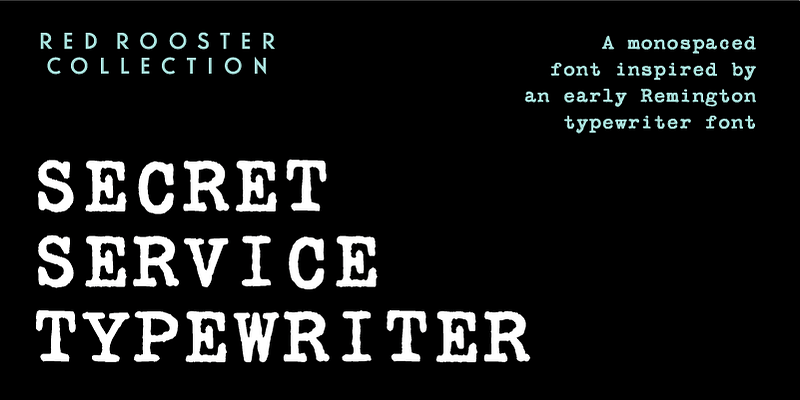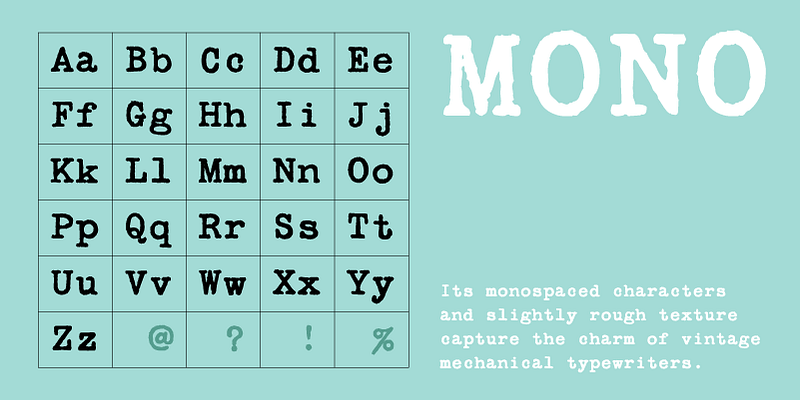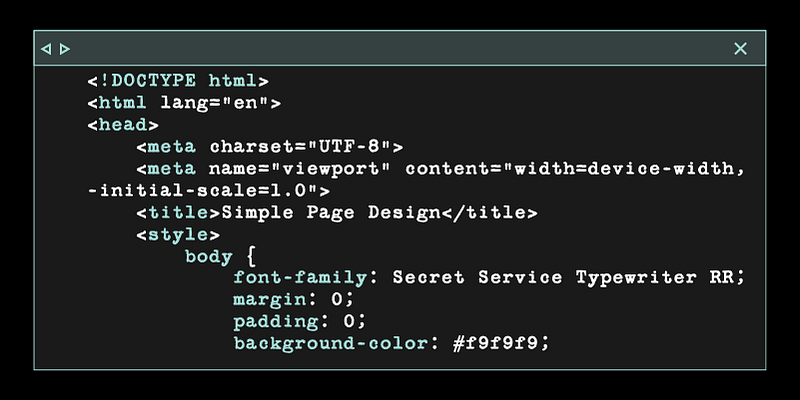
Die Secret Service Typewriter ist inspiriert von der Schreibmaschinenschrift Remington der Keystone Type Foundry aus dem Jahr 1905. Die nichtproportionalen Zeichen (Monospace) und die leicht raue Textur vermitteln den Charme alter mechanischer Schreibmaschinen mit ihrer charakteristischen Unvollkommenheit. Diese Schrift verleiht Designs einen Hauch von Retro oder Nostalgie und eignet sich hervorragend für Themenmagazine, Plakate, Retro-Markenidentitäten oder Museumsausstellungen zum Thema Spionage.